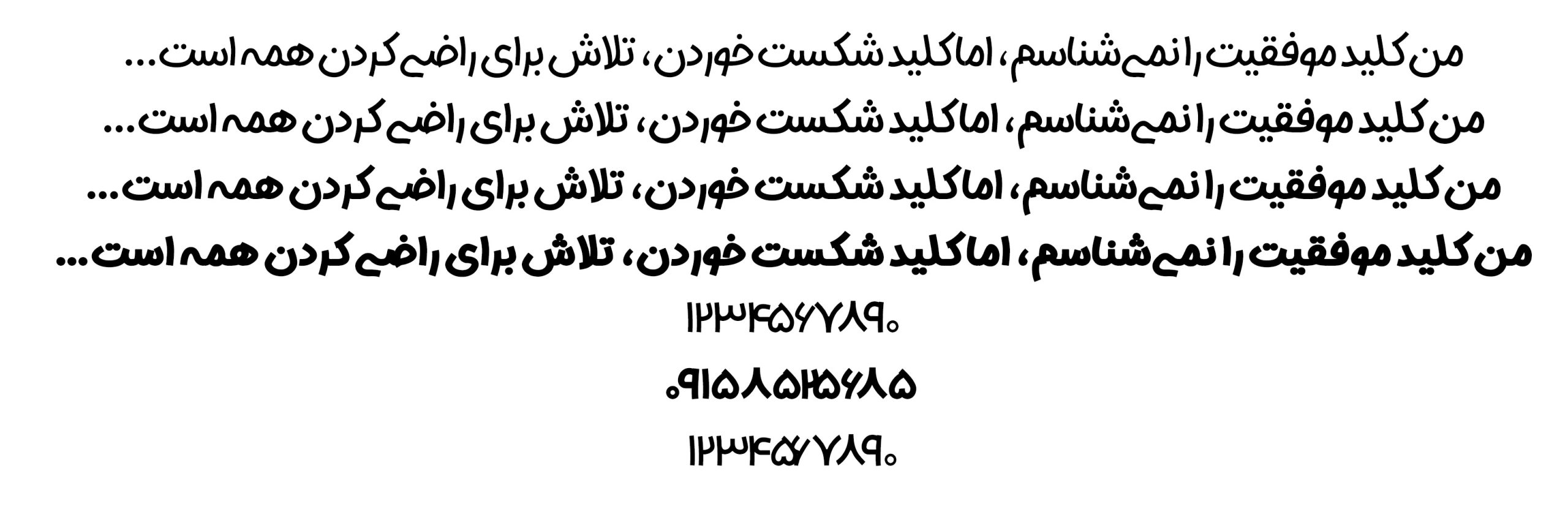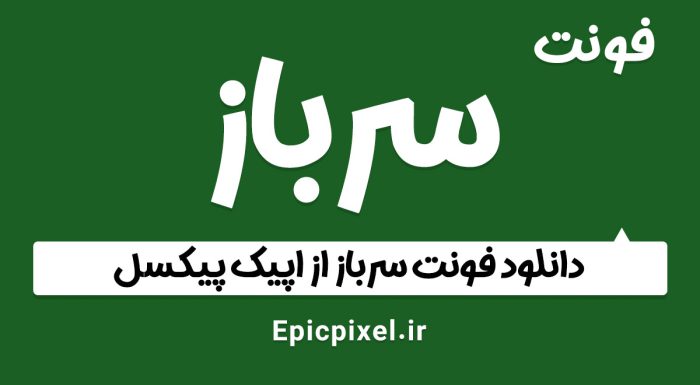
5 فونت سرباز فارسی
فونت سرباز: یک قلم فارسی منحصر به فرد و مدرن
فونت سرباز یکی از جدیدترین و زیباترین قلم های فارسی است. این فونت با داشتن ساختاری منظم و نرم، لیگچرهای متنوع و زیبا، قابل استفاده در تمام پلتفرم ها، کاربردهای گسترده در زمینه های مختلف، به یکی از پرطرفدارترین قلم های فارسی تبدیل شده است. در این مقاله قصد داریم به معرفی فونت سرباز و طراح آن، ویژگی های این فونت، کاربردهای آن، نحوه خرید و نصب آن، نظرات کاربران درباره آن و نتیجه گیری و پیشنهادات بپردازیم.
معرفی فونت سرباز و طراح آن
فونت سرباز یک قلم فارسی الهام گرفته از حروف دست نویس که در سال 1398 طراحی شده است.
ویژگی های فونت سرباز
فونت سرباز با داشتن ویژگی های منحصر به فرد خود، توانسته است جایگاه خود را در بین قلم های فارسی پیدا کند. برخی از این ویژگی ها عبارتند از:
ساختار منظم و نرم
فونت سرباز یک قلم با ساختار منظم و نرم است که الهام گرفته از حروف دست نوشته است. این فونت با داشتن خط های روان و ملایم، به متن یک حالت زنده و جذاب می بخشد. فونت سرباز در یک وزن طراحی شده است که در آپدیت بعدی سایر وزن های آن نیز ارائه خواهد شد. این فونت شامل تمامی حروف از الف تا ی و اعداد فارسی در تمامی حالات است.
لیگچر یک حالت خاص از نمایش حروف است که در آن دو یا چند حرف با هم ترکیب شده و به صورت یک علامت جدید نمایش داده می شود. لیگچرها معمولا برای زیباسازی متن و جلوگیری از تکرار حروف استفاده می شود. فونت سرباز با داشتن حدود 50 لیگچر مختلف، به متن یک حالت منحصر به فرد و خلاقانه می دهد. برای استفاده از لیگچرهای فونت سرباز، کافی است که در نرم افزار فوتوشاپ دکمه لیگچر را روشن کنید.
قابل استفاده در تمام پلتفرم ها
فونت سرباز یک قلم با قابل استفاده در تمام پلتفرم های مختلف است. شما می توانید این فونت را در تمام نسخه های ویندوز، مک، ios، اندروید و وب به راحتی نصب و استفاده کنید. فونت سرباز با دقت بالای خود، در هر سایز و رزولوشنی به خوبی نمایش داده می شود.
کاربردهای فونت سرباز
فونت سرباز یک قلم با کاربردهای گسترده و متنوع است که می تواند در زمینه های مختلف استفاده شود. برخی از این کاربردها عبارتند از:
کمپین تبلیغاتی و هویت سازمانی
فونت سرباز یک قلم مناسب برای استفاده در کمپین های تبلیغاتی و هویت سازمانی است. این فونت با داشتن حالت زنده و جذاب، می تواند به ارائه پیام های تبلیغاتی و ارتباط برقرار کردن با مخاطبان کمک کند. فونت سرباز با داشتن لیگچرهای زیبا، می تواند به ایجاد یک هویت منحصر به فرد و ممیز برای برند ها و سازمان ها کمک کند. برخی از نمونه های استفاده از فونت سرباز در کمپین های تبلیغاتی و هویت سازمانی عبارتند از: لوگو و آرم شرکت های مختلف، بروشور و پوستر تبلیغاتی، بسته بندی محصولات، کارت ویزیت و … .
نشریات و برنامه های تلویزیونی
فونت سرباز یک قلم مناسب برای استفاده در نشریات و برنامه های تلویزیونی است. این فونت با داشتن خط های روان و ملایم، می تواند به خوانایی متن ها و جذب توجه خوانندگان و بینندگان کمک کند. فونت سرباز با داشتن لیگچرهای خلاقانه، می تواند به اضافه کردن جذابیت و حس خود به خود به محتوا کمک کند. برخی از نمونه های استفاده از فونت سرباز در نشریات و برنامه های تلویزیونی عبارتند از: عناوین و مقالات روزنامه ها و مجلات، تصاویر و گراف های نشان داده شده در صفحه نمایش، لوگو و آرم برنامه های تلویزیونی و … .
فونت سرباز یک قلم مناسب برای استفاده در بازی ها و نرم افزار ها است. این فونت با داشتن ساختار منظم و نرم، می تواند به رابط کاربری یک حالت زیبا و کارآمد بدهد. فونت سرباز با داشتن قابل استفاده در تمام پلتفرم ها، می تواند به سازگاری بازی ها و نرم افزار ها با دستگاه های مختلف کمک کند. فونت سرباز با داشتن لیگچرهای متنوع و زیبا، می تواند به اضافه کردن شخصیت و جذابیت به بازی ها و نرم افزار ها کمک کند. برخی از نمونه های استفاده از فونت سرباز در بازی ها و نرم افزار ها عبارتند از: منو، دکمه، عنوان، زیر نویس، پیام، اسکور، آچیومنت و … .